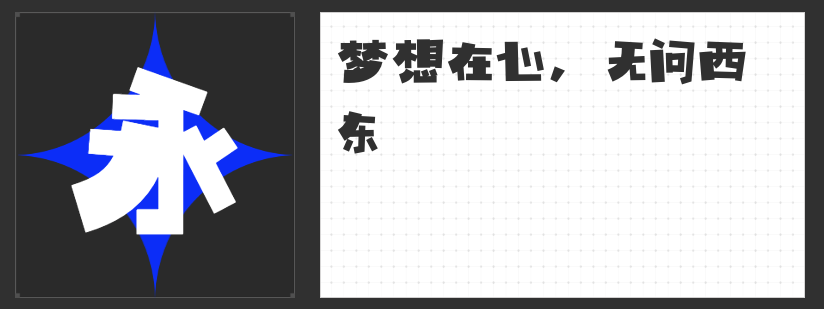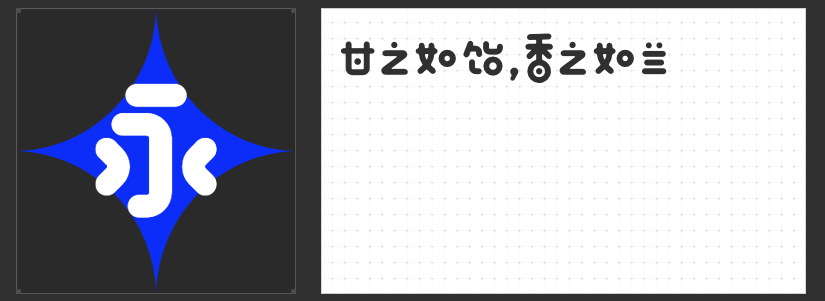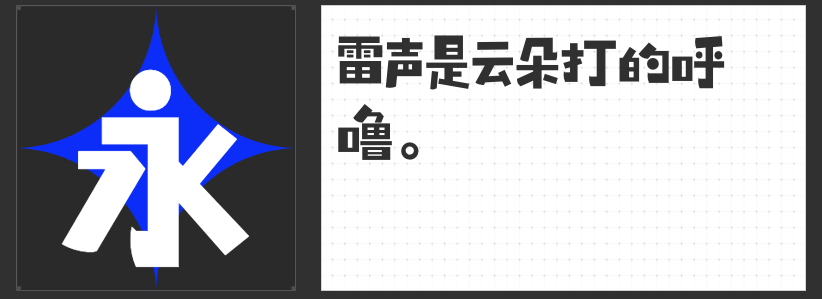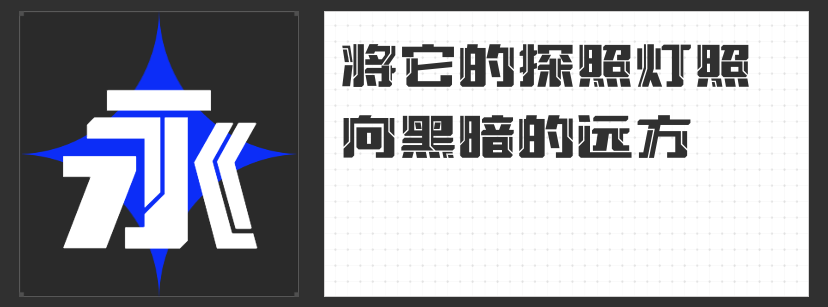
四款创意字体推荐:解锁设计中的视觉革新力量
在平面设计的创意疆域中,字体早已突破信息载体的单一功能,成为传递情感、塑造风格的核心元素。当常规字库难以满足个性化表达需求时,一批兼具艺术性与实用性的创意字体应运而生。以下四款各具特色的字库字体,以突破性的设计语言为设计注入新鲜灵感。
一、高手兵克战甲体
这款字体将工业设计的机械感融入字形结构,通过直线花纹的叠加构建出类似机甲外壳的视觉效果。每个字符都如同精密零件,笔画间的切割感与力量感形成强烈冲击。其独特的设计语言尤其适合科技、游戏或未来感主题的设计项目,能以硬朗的视觉姿态瞬间抓住观者注意力。
二、创客贴软糖体
突破传统字库的刻板框架,创客贴软糖体采用等粗线条与动态字框设计,在保持文字可读性的同时赋予排版前所未有的灵活性。相同字号下宽高比例的自然变化,使文字排列既能形成整齐的韵律感,也可通过手动调整创造错落有致的视觉节奏。这种“可塑字体”特性为设计师提供了更大的创作自由度。
三、万人字造拾梦简 超级黑
这款艺术字体在保留手写温度的基础上进行结构解构,左粗右细的笔画对比与疏密有致的布局,营造出动态平衡的视觉美感。曲线元素的巧妙融入打破了直线构图的单调,随性而不失识别性的笔画摆放,让文字在传递信息的同时成为画面中的装饰元素,适合需要营造人文氛围的设计场景。
四、喵字海报体
专为海报场景打造的细分字库,通过非常规的混搭排版策略突破传统布局范式。错落有致的字符排列与实验性的风格融合,既保证了远距离的可读性,又以灵动多变的视觉语言契合年轻化品牌的传播需求。这款字体如同会呼吸的文字,能为品牌注入鲜活的个性基因。
当设计陷入同质化困境时,这些突破常规的创意字体恰似一剂强心针。它们以独特的形态语言重新定义文字的可能性,让每个字符都成为传递态度的视觉符号。